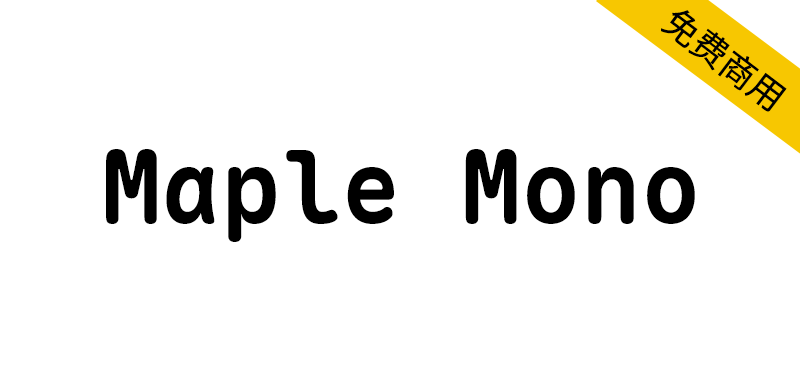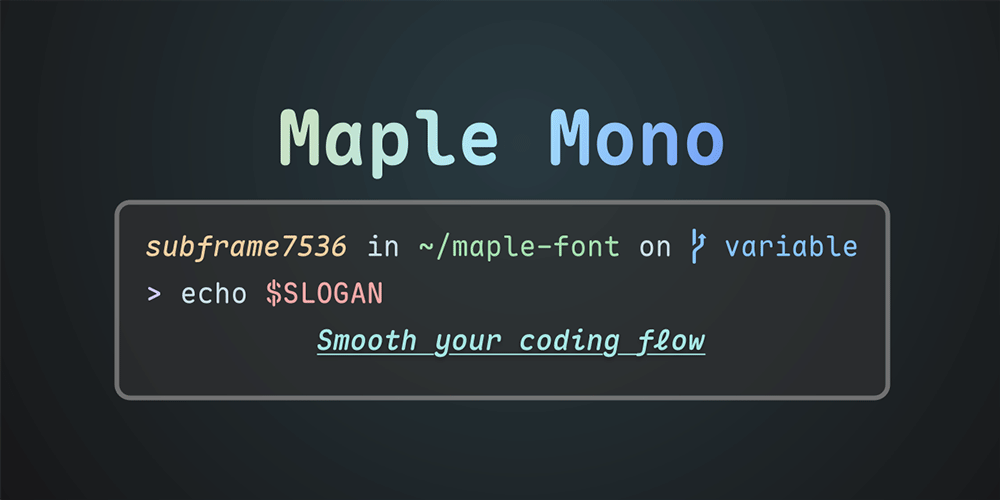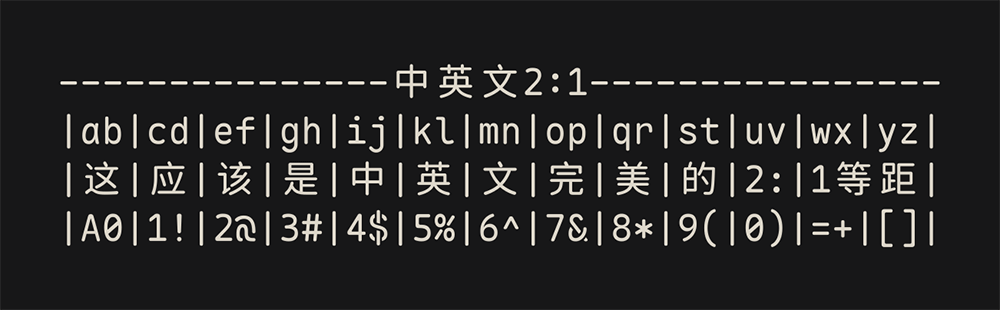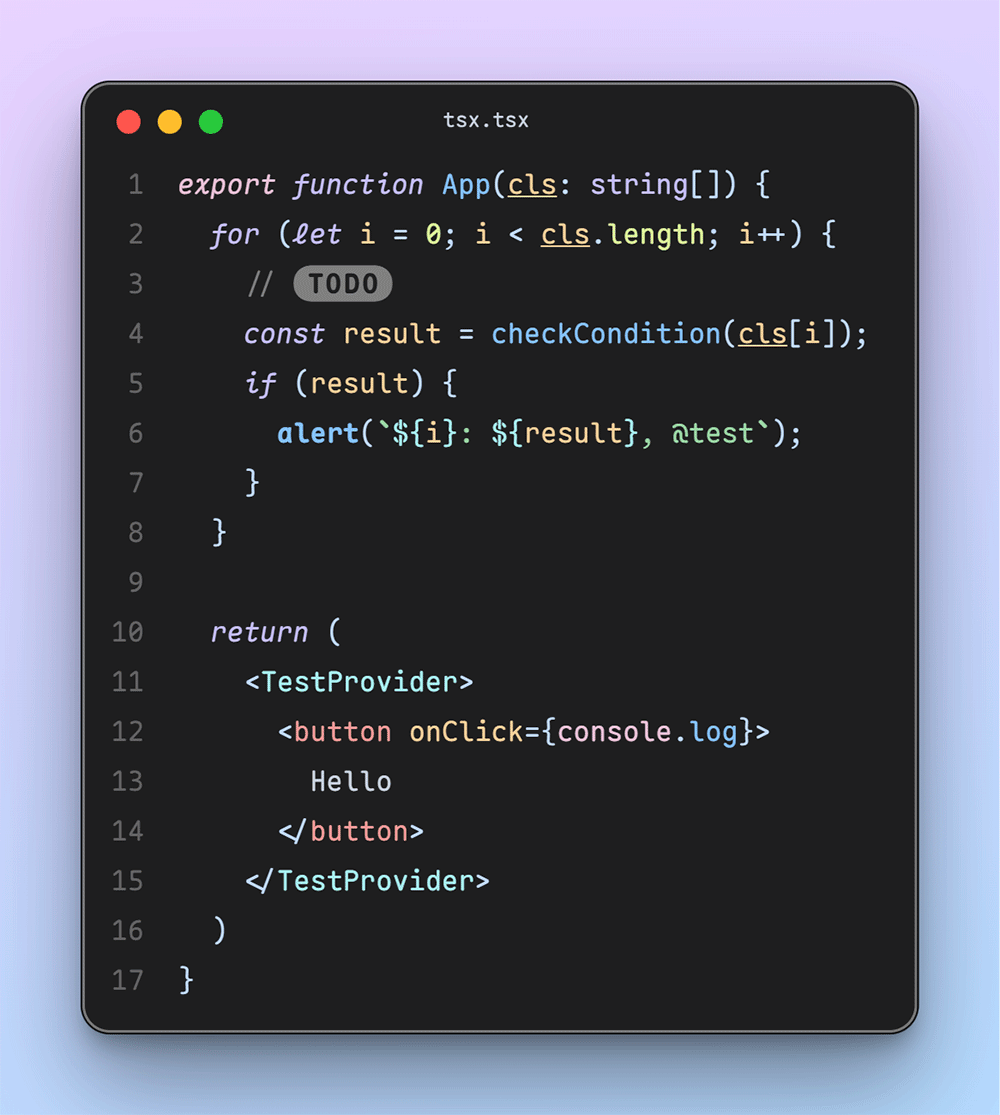
Maple Mono 是一种开源的带连字和控制台图标的圆角等宽字体,中英文宽度完美2:1,专注于平滑您的编码流程。我创建它是为了增强我的工作经验,并希望它对其他人有用。
特征:可变-具有细粒斜体字形的无限字重;平滑-圆角,全新的@$%&Q->字形和斜体草书f i j k l x y;有用-大量智能连字;Icon,一流的Nerd-Font支持,让您的终端更加生动;自定义-根据需要启用或禁用字体功能,只需创建自己的字体即可。
支持简体中文、繁体中文和日文:CN版本包含简体中文、繁体中文和日语的字形,这些字形不像大多数CN字体那样正常。CJK字形的间距要宽松得多,以便更好地进行度量对齐。